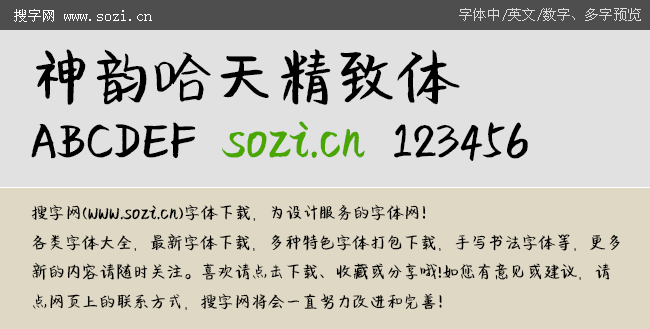
神韻哈天精致體
搜字網(wǎng)提供一款神韻哈天精致體中文書法字體下載,神韻哈天精致體是一款手寫風(fēng)格的書法字體,字體書寫流暢,字形大方,整體效果十分出色,適合應(yīng)用于廣告設(shè)計(jì)、名片設(shè)計(jì)、包裝印刷、產(chǎn)品設(shè)計(jì)等應(yīng)用。